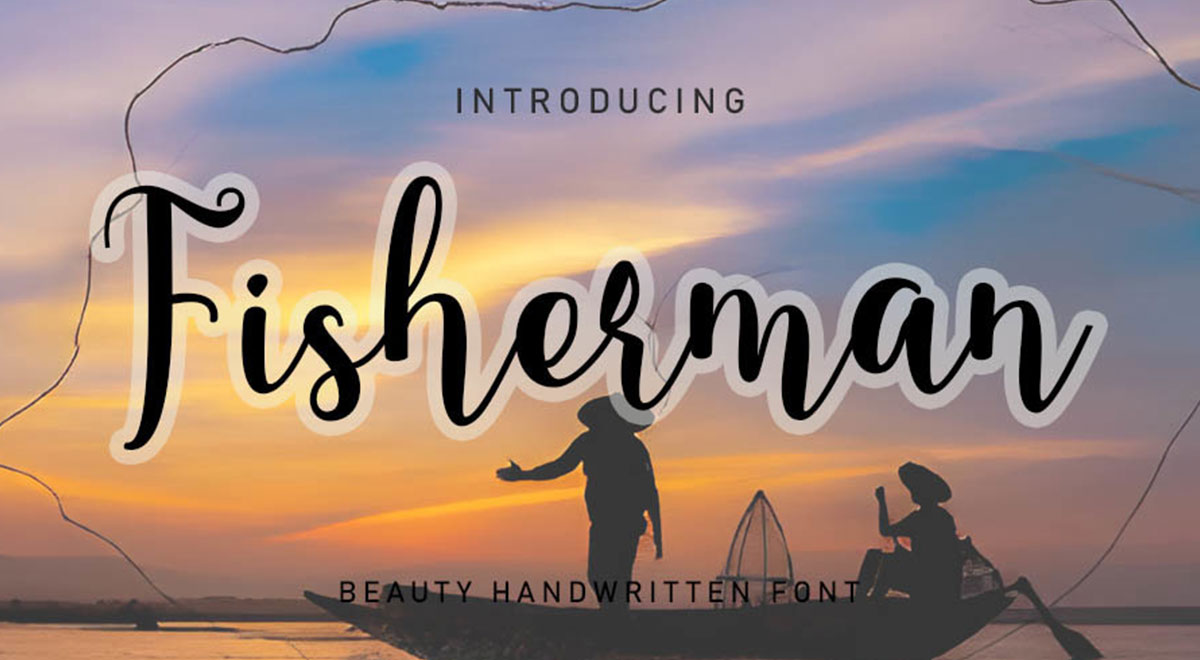
فونت Fisherman انگلیسی
دانلود فونت Fisherman انگلیسی Font فیشرمن |
| ⭐ مجموعه فونت | دانلود فونت انگلیسی ماهیگیر Font Fisherman |
| ⭐ توضیحات | فونت Fisherman Font را معرفی میکنیم، خطی و حروف دستنویس عجیب و غریب و ارگانیک که جوهر یک ماجراجویی بیخیال ساحلی را به تصویر میکشد. این فونت با خطوط روان و شخصیت بازیگوش خود، حس شادی و آرامش را به طرح های شما می بخشد. فونت ماهیگیر که برای طرحها، آرمها و پروژههای برندسازی با مضمون ساحلی ایدهآل است، جذابیت ساحلی را اضافه میکند و روح خلاقیت دستنویس را به تصویر میکشد و باعث میشود متن شما به اندازه نسیم دریا احساس طراوت کند. |